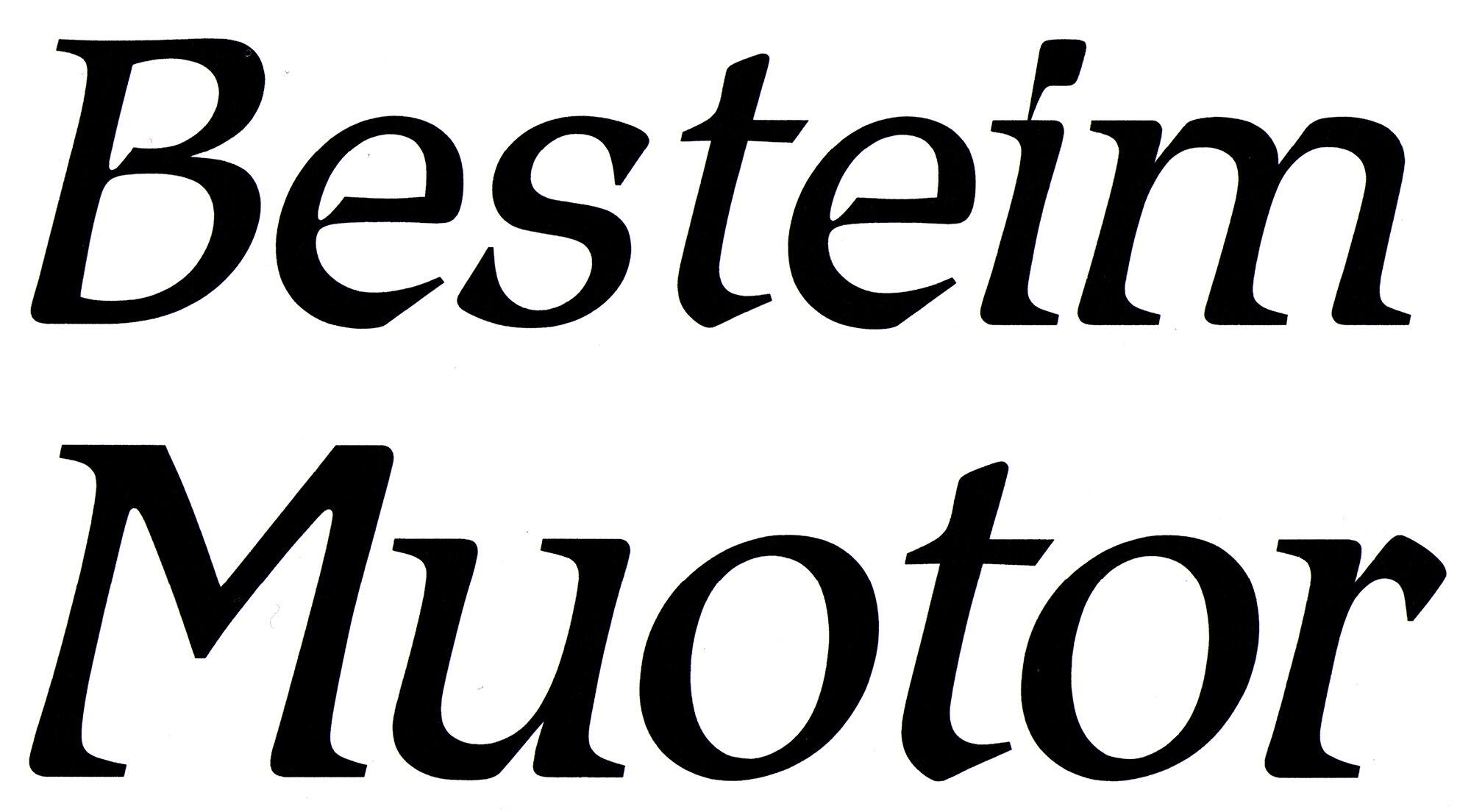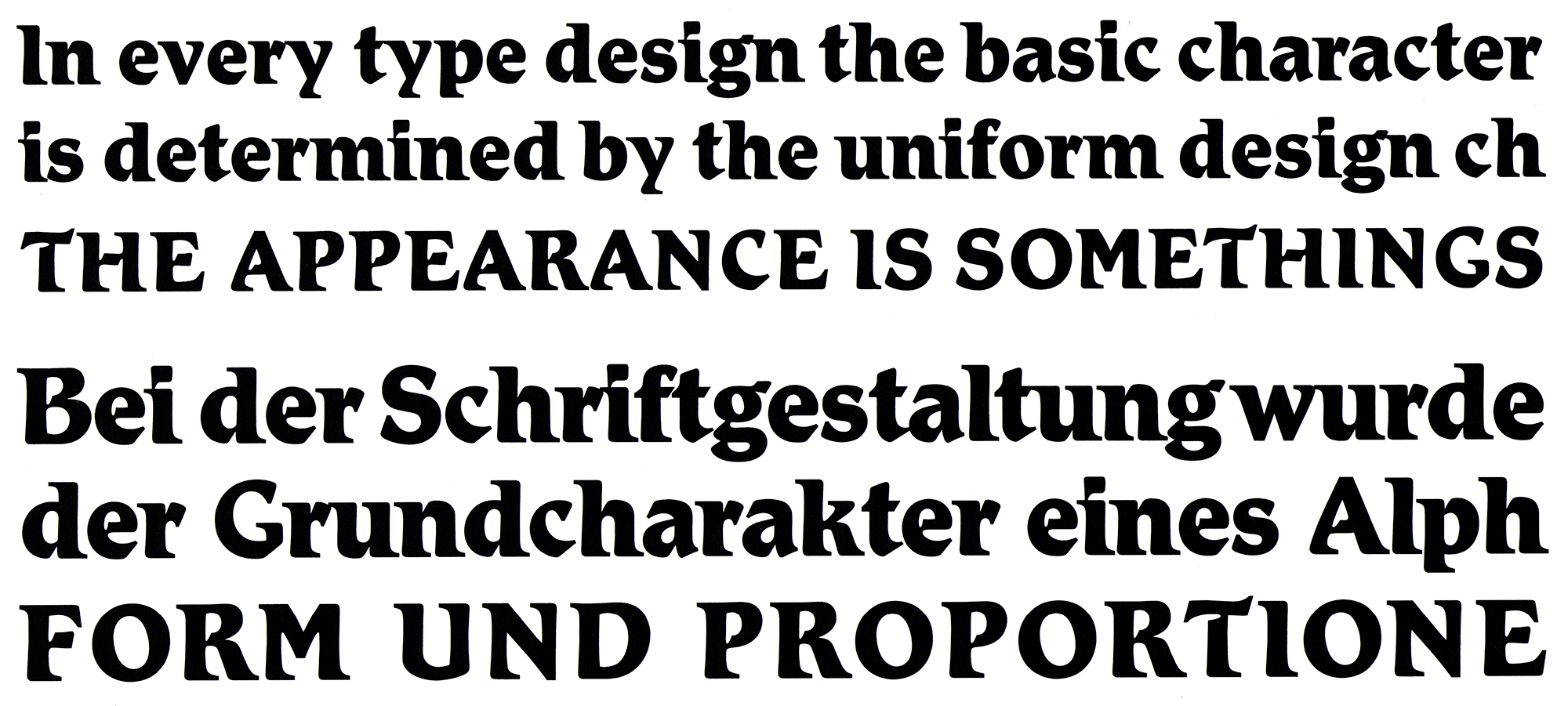
Die Romic von Colin Brignall erschien 1980 als Fotosatzschrift über die International Typeface Corporation. Zur Familie zählen ein Roman-Schnitt mit zugehöriger Kursive in Oblique-Optik und drei schmaler laufende Strichstärken (medium, bold, extra-bold) ohne Kursive.